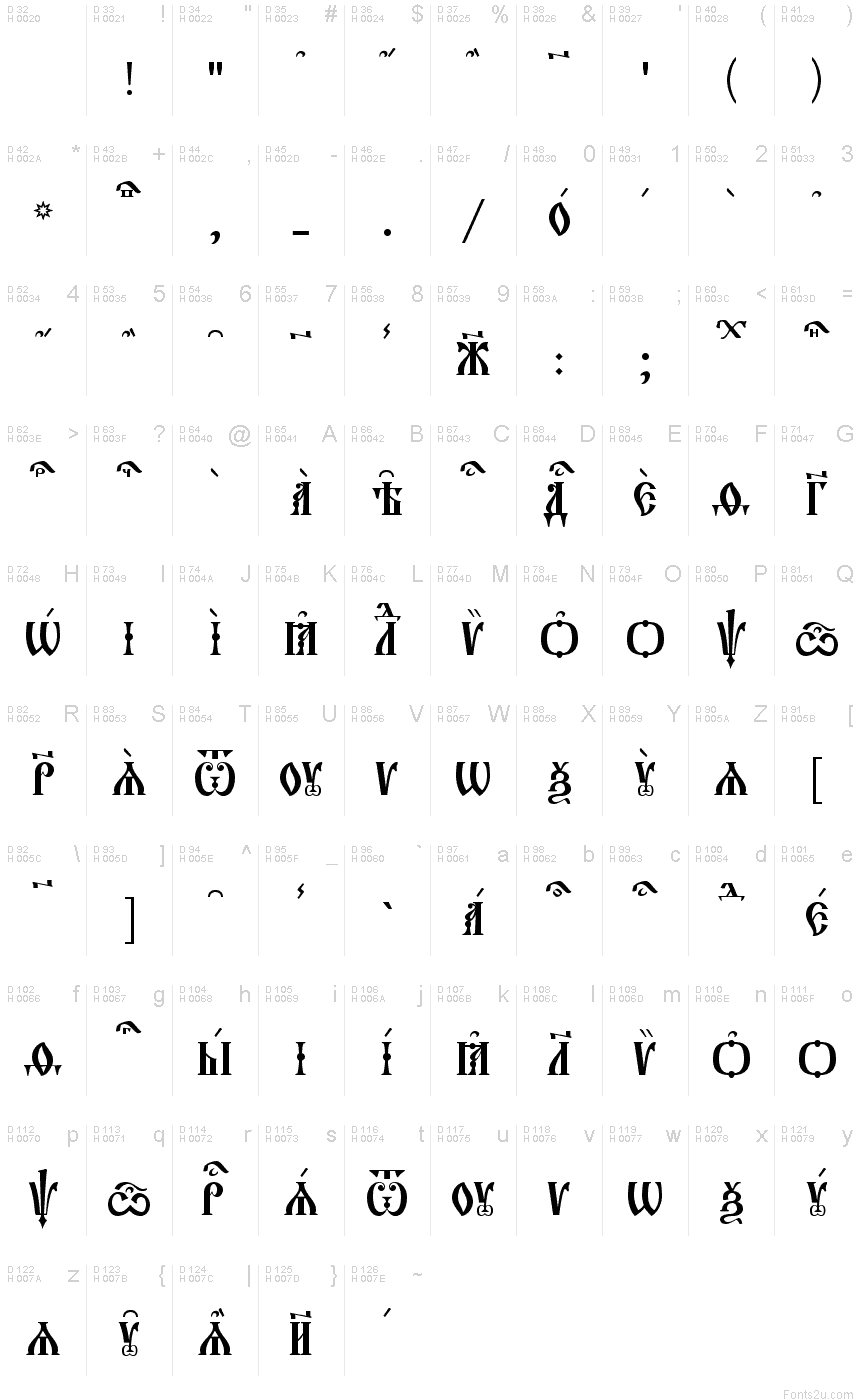
Orthodox TT UCS8 Caps, di SoftUnion Ltd e N. Andrushchenko, è un font cirillico ortodosso gratuito che richiama l'aria solenne e ornamentale della scrittura ecclesiastica. Le lettere uniscono forme ampie e pesanti a rotondità a goccia, dettagli a forma di croce e tratti interni curvi, rendendo il set cerimoniale piuttosto che puramente storico.
Si adatta a progetti che richiedono una voce liturgica o slava antica: icone, bollettini parrocchiali, copertine di libri, poster culturali e cartelli di titoli sono perfetti per questo font gratuito. Usalo dove poche parole possono definire lo stile, perché le maiuscole decorate hanno un carattere rituale sufficiente per reggersi da sole in intestazioni, iniziali e marchi simili a monogrammi.
Orthodox font is intended for publishing liturgical texts in Church Slavonic language. This font created on the basis of the font Evangelie by N. Andrushchenko